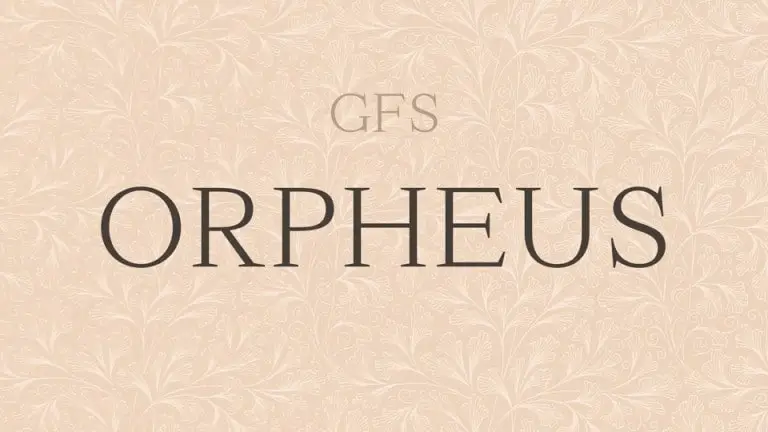
GFS Orpheus Serif Font – Download Grátis
A GFS Orpheus Serif Font é uma elegante escolha para qualquer projeto que exija um estilo serif clássico moderno. Seu uso imediato inclui banners, anúncios e logotipos, mas também se adapta perfeitamente a jornais e revistas, perfumaria e até mesmo moda. Inspirada no texto de um antigo livro escolar intitulado “Στοιχειώδης Φυσική Ιστορία”, publicado em 1887 pela editora Anestis Konstantinidis em Atenas, essa fonte oferece uma gama de alternativas estilísticas que lhe permitirão personalizar suas criações sem deixar nada ao acaso. Com seu formato todo em maiúsculas e alternativas estilizadas, a GFS Orpheus Serif Font tem o poder de satisfazer a maior variedade de projetos visuais, tornando-a uma fonte ideal tanto para iniciantes quanto para profissionais ávidos por imprimir sua marca.